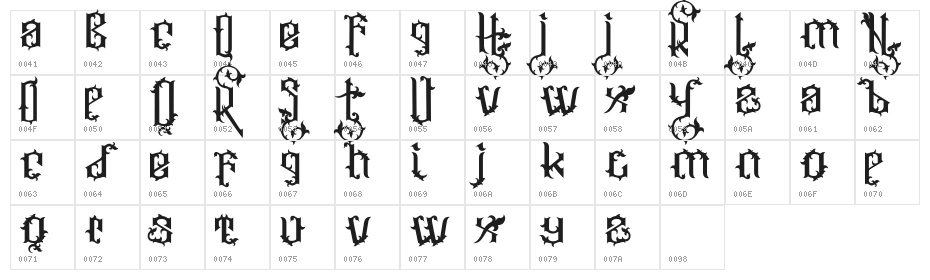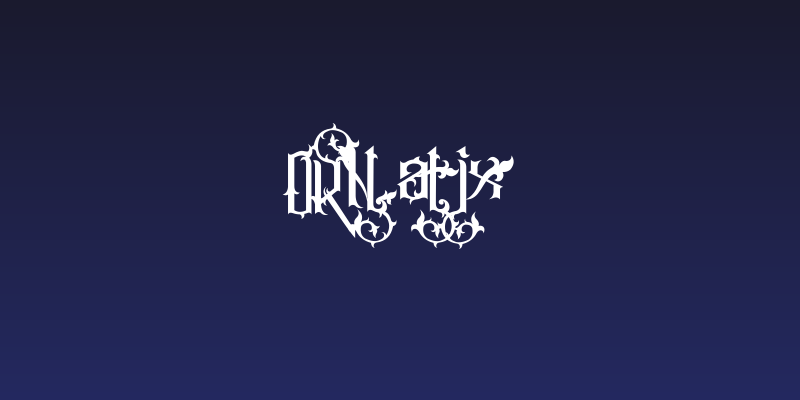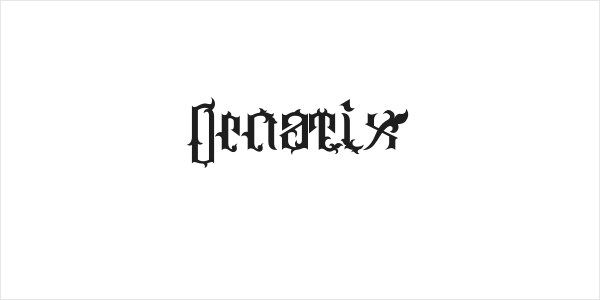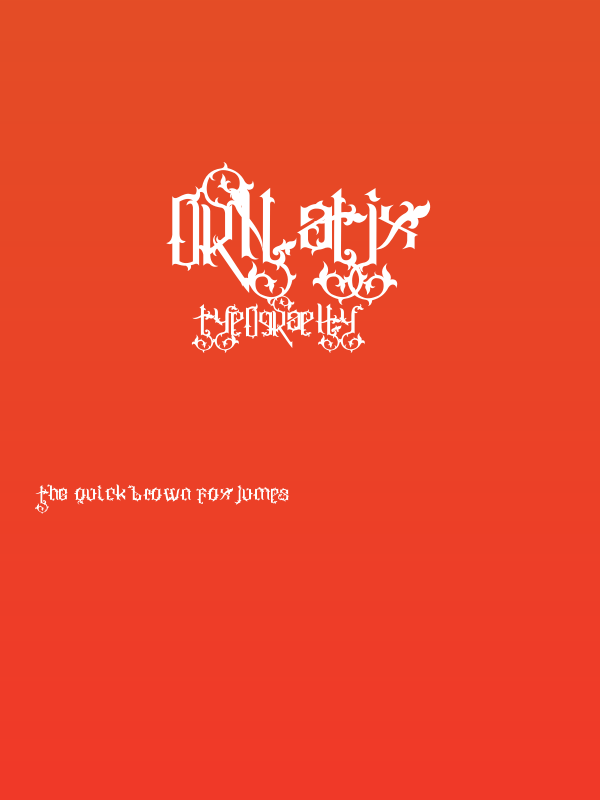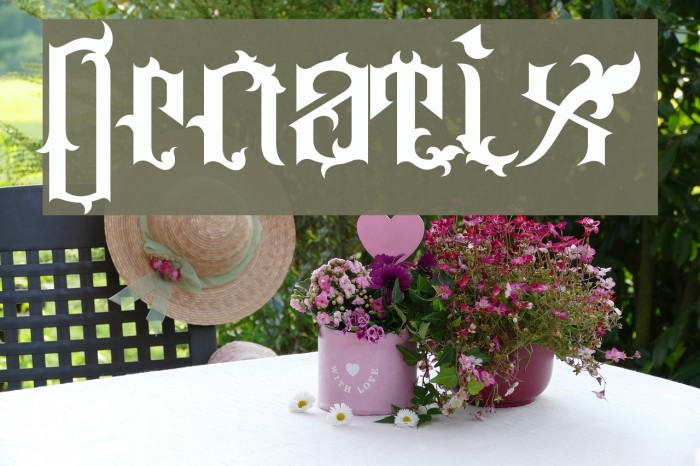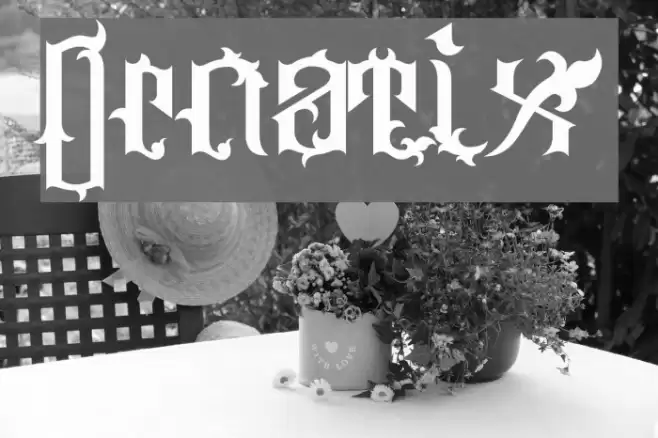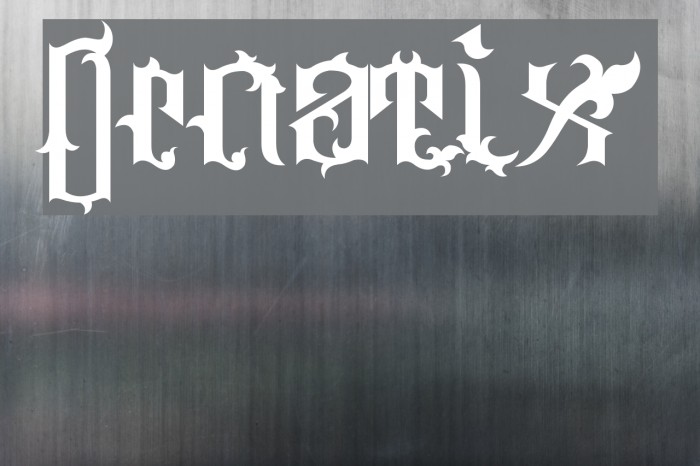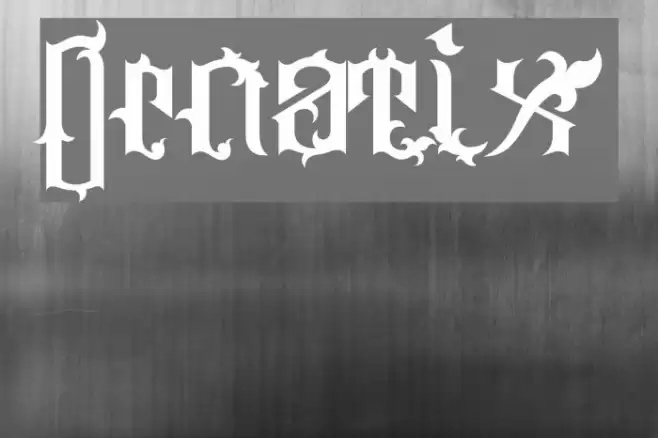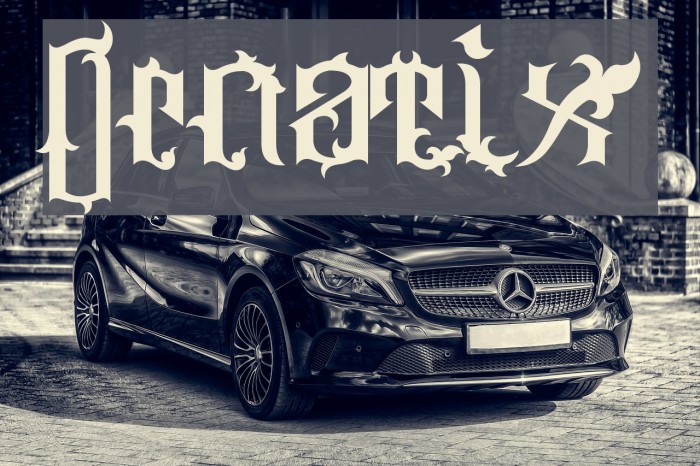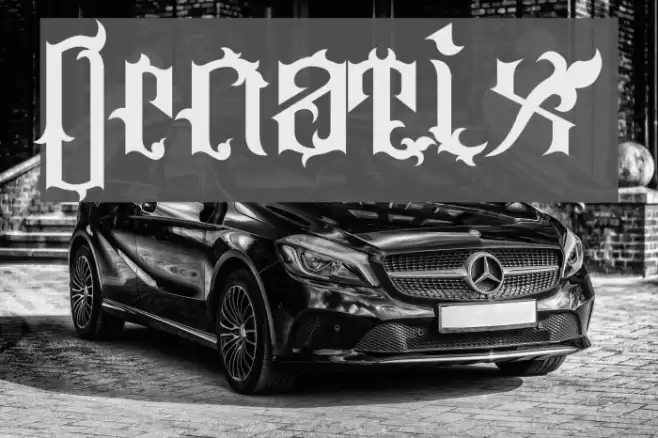
Ornatix Font
✎ Gothic
| Progetti proposti | Ideal for fantasy-themed designs, historical event posters, book covers, or any project requiring a dramatic, medieval aesthetic. |